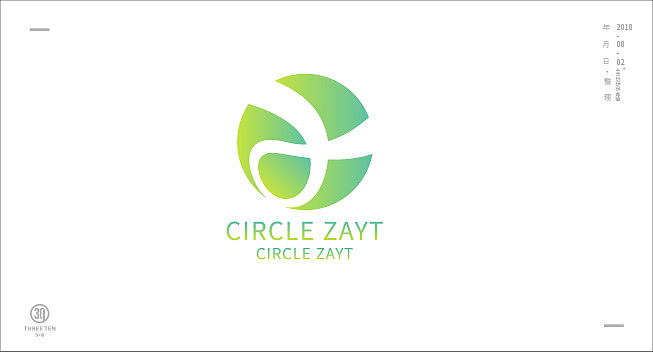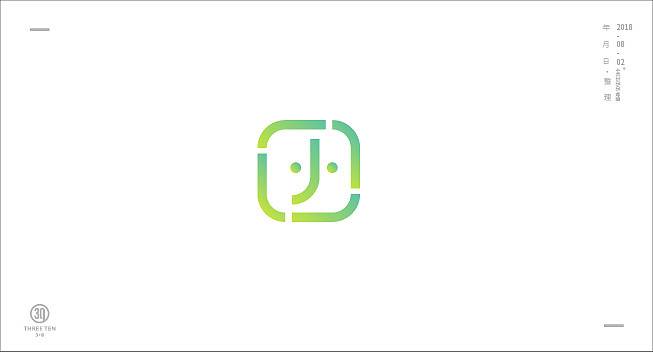
字体图形logo
时间总能让你忘记点什么,
也能想你想起点什么。
忘记,
可能是一些没有记忆的东西,自然而然就忘记了,也许是好,也许是不好。
回忆,
可能是一些事情在记忆中产生了回忆,让你无法忘记,
可能是开心的大笑、伤心的痛,经历的成长。
这回忆不一定是美好的,
一定是你经历的,但是想忘记,
那就只能不去回忆,
让他封存下来。
一股草绿色图形。